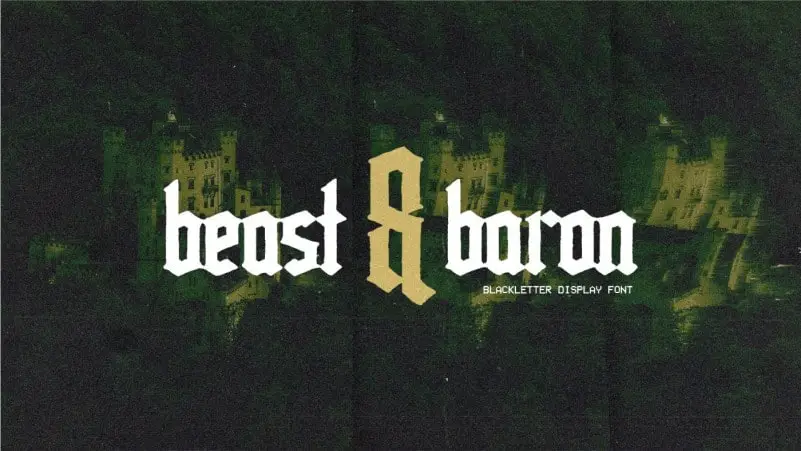
Beast & Baron Blackletter Font – Download Grátis
A Beast & Baron Blackletter Font é uma excelente escolha para quem busca uma fonte única e autêntica que transmite uma atmosfera arrepiante. Criada pelo designer Caleb Brand na plataforma 99designs, esta fonte blackletter traz um toque moderno à tradição de tipografia rugged. Com seu aspecto desorganizado e cuidadosamente feito à mão, ela é perfeita para aplicações que necessitam de uma identidade visual única, como logotipos ou rótulos de embalagens. Com um ar vintage que se atualiza com linhas modernas, esta fonte captura a essência dos tempos góticos e renais, enquanto traz uma nova energia para o mundo contemporâneo. Seria uma escolha inteligente para qualquer projeto que busque dar um toque especial à sua identidade visual ou design de marca.